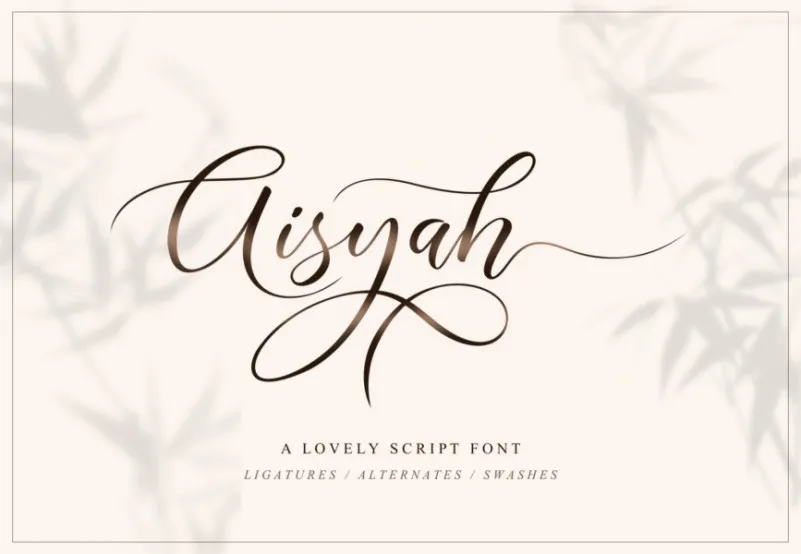
Aisyah Script Font – Fonte Grátis
Aisyah Script Font
Descubra Aisyah Script Font, uma elegante fonte que combina sofisticação com delicadeza. Introduzida pelo estúdio Ghuroba Studio, essa fonte é perfeita para aqueles buscando um estilo único e sofisticado. Com seu traçado refinado, Aisyah Calligraphy Script torna-se a escolha ideal para qualquer projeto de design, garantindo uma elegância eterna em cada caractere. Imagine ter o luxo de usar sua própria assinatura ou logo personalizado em todas as suas mídias digitais e impressos. Este é um verdadeiro presente para os amantes da fonte, proporcionando facilidade no processo de criação e tornando a personalização do seu projeto mais deslumbrante. Aisyah Script Font oferece o que há de melhor na mixagem de elegância e delicadeza, uma experiência inigualável para quem busca agregar sofisticação em cada projeto visual.